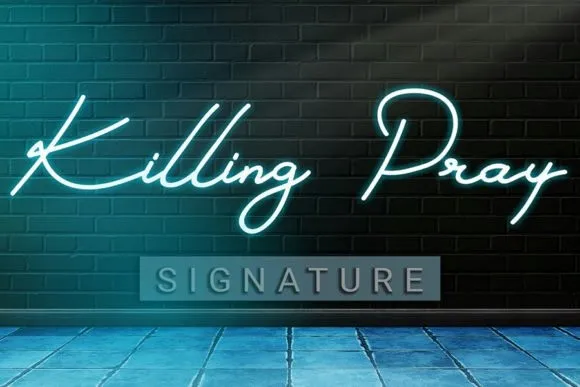
Killing Pray Font – Download Grátis
A fonte ‘Killing Pray Font’ é uma maravilha no estilo de letra script monoline com uma sensação autêntica e casual. Ela foi criada pelo designer Mr.Soon Design, uma marca que oferece um toque elegante, mas ao mesmo tempo descontraído e versátil. Seu uso pode ser amplamente adaptado a diversos fins como logotipos, convites de casamento, subtítulos, camisetas, carimbos, placas de sinalização, rótulos, noticiários e até mesmo postais. Essa fonte não só enriquece o design gráfico com seu aspecto moderno e contemporâneo, como também permite uma personalização única para qualquer projeto que você está criando. Composta para se adaptar facilmente em diferentes tamanhos e formatos, ela é um recurso essencial tanto para designers profissionais quanto para iniciantes que buscam adicionar um toque único a seus trabalhos.